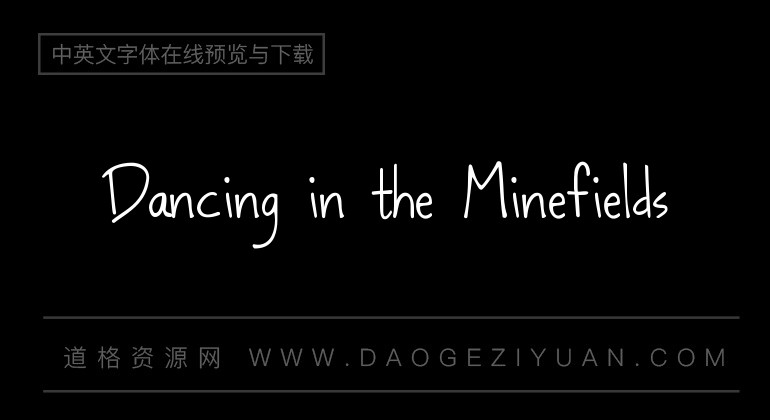
"Dancing in the Minefields" 字体是一种手写风格的字体,由字母和数字组成。它的特点是非常自然、流畅而且有点带有随意感。这种字体看起来就像是手写在纸上的一样,给人一种个性化和亲切感的印象。它适用于卡片、海报、标志、T恤等设计中,特别是在需要表现随意、慵懒或轻松愉快的情境下,这种字体非常适合使用。内容介绍
Dancing in the Minefields是一款非常不错的手写艺术字体,具有很好的视觉感,适合于文化类的宣传设计、商业类品牌的广告和产品包装设计以及个性化文字排版等较多场景。